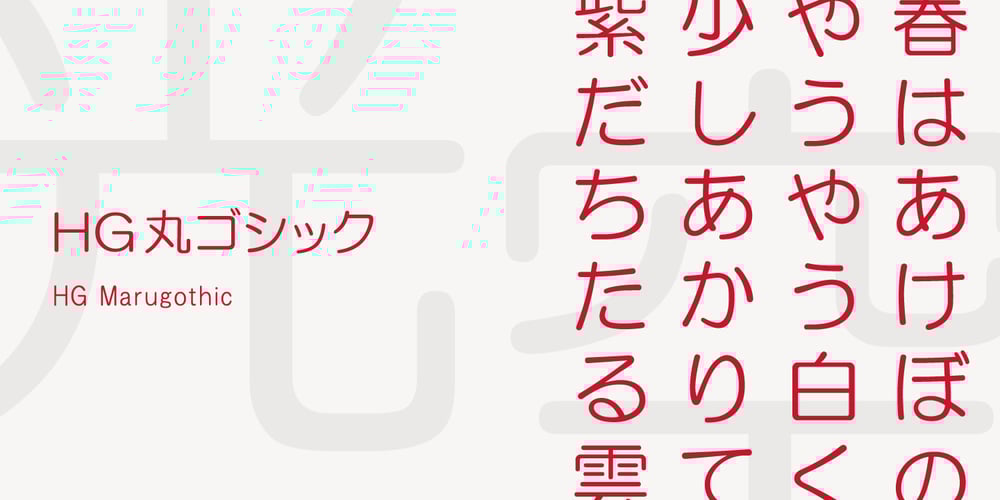
HG Marugothic
HG Marugothic font
HG Marugothic Font Family was designed by published by RICOH. HG Marugothic contains 3 styles and family package options. HG丸ゴシックは、リョービの書体「シリウス」を字母とする丸ゴシック体です。L、M、Bと、3つの太さがあります。線はやわらかで、全体的に明るく、あたたかさがあります。ふところは大きくとられていて、かつ、仮名も大きめに作られていて、判別もしやすくなっています。また、それらの特徴から、カジュアルな印象を強く与えますが、ややコントラストがあるため、すっきりとしていて、優しい印象も与えます。